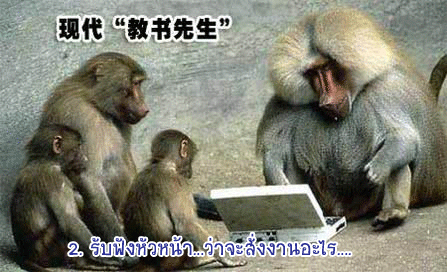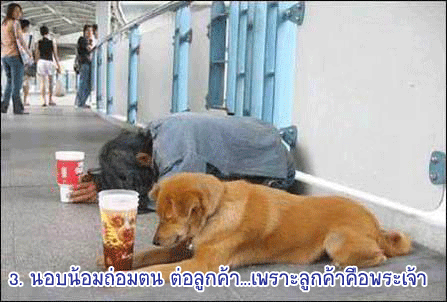
ฟ๐นต์นี้ทำตัวใหญ่ๆ ไม่สวยเลย :05:
แต่สำนักพิมพ์นี้ชอบฟอนต์นี้มากเลยนะ
ไปเจอบนเว็บ นสพ.ไทยรัฐ
โครงการของ สสส เขาล่ะมั้ง
แอบขโมยฟนต์เด็กแถวๆ นี้ไปใช้งานก่อนนะจ๊ะ  :42: